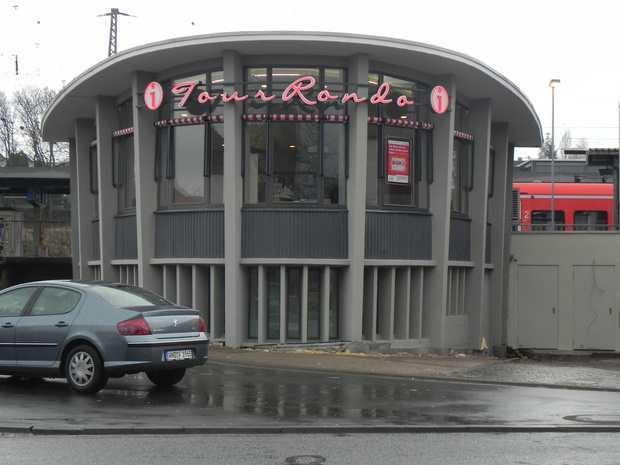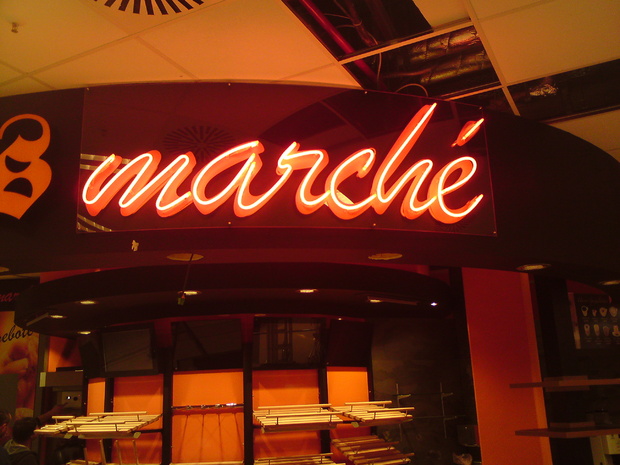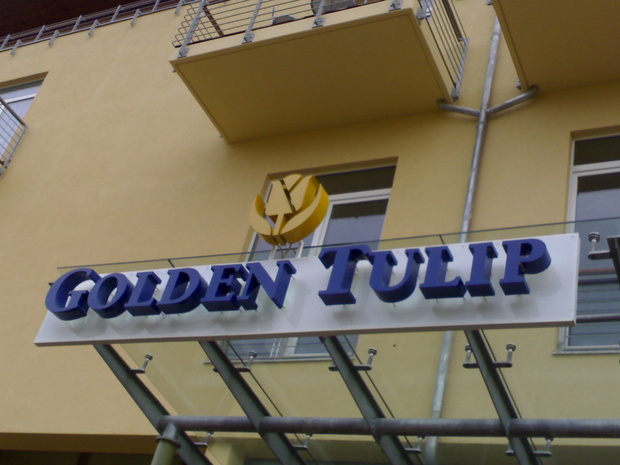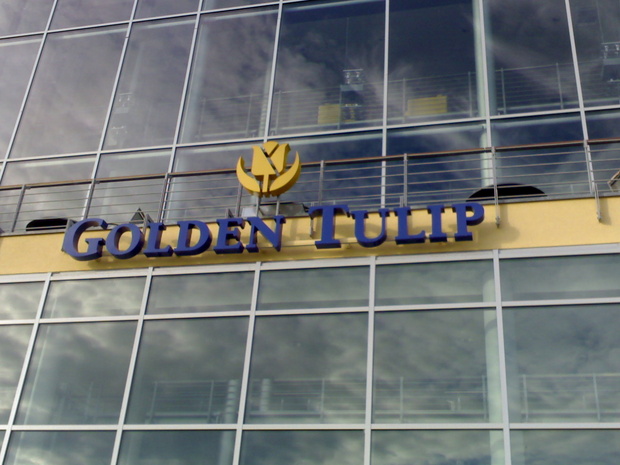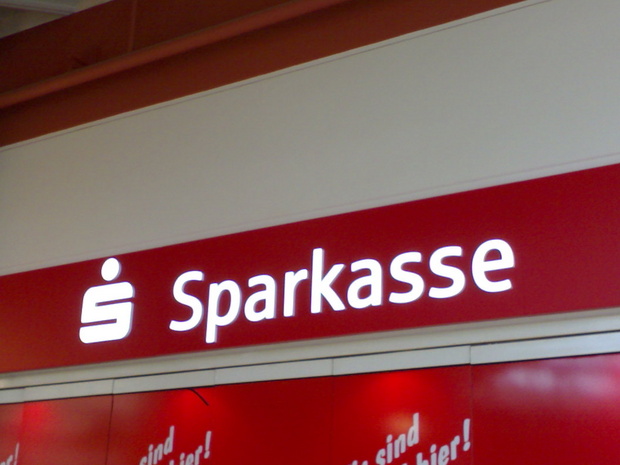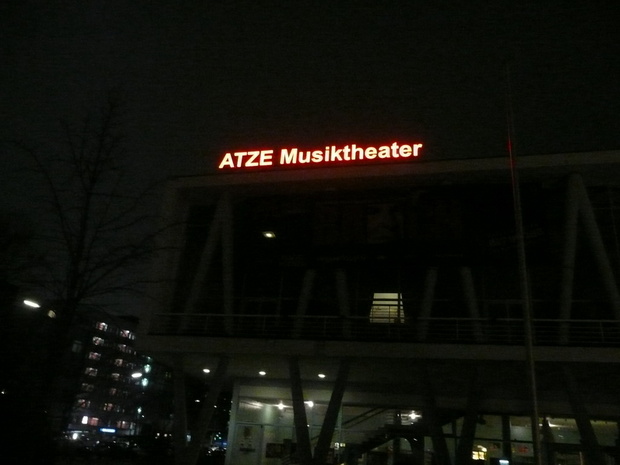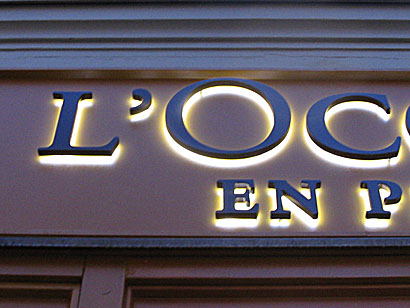
passende Schrift für Hotelbeschriftung gesucht
Hallo liebe Typografinnen und Typografen!
Ich bin dabei ein Hotel zu eröffnen und suche für die Außen-Beschriftung eine passende Schrift. Könntet ihr mir dabei behilflich sein?
Vielen Dank für jede Idee!
Marius Neusteff
Hallo Herr Neusteff,
ich mache professionelle Licht- und Leuchtwerbung in allen Variationen. Angefangen von Acrylglas, mit Neon o. LED, Edelstahl, Kupfer, Titan etc..
Alle Formen und Variationen sind denkbar. Eine edle Variante ist das sogenannte Profil 3-nach hinten an die Fassade strahlend. Nachteil ist dass in der Fernsignalsiation dies nicht so gut lesbar und klar ist wie das Profil 5 nach vorne leuchtend..
Eine KLARE deutliche Schrift erhöht die Lesbarkeit (wichtig z. B. wenn die Autobahn 1 km weit entfernt ist und der Name dort lesbar sein soll)
Denken wir an die vielen einfachen "H O T E L "-Schriftzüge...
Wenn Sie eine schöne Schrift nehmen möchten (z. B. Schreibschrift) wäre das eher was für den Nahbereich, also am Eingang.
Anbei mal ein Bild meines letzten Projektes - natürlich mit Ralfs "i" :)
Anbei mein letztes Projekt (einige erinnern sich noch als ich die passende 50er Jahre Schreibschrift suchte..)
Die Metallbuchstaben (wie in bertels Beispiel) finde ich wesentlich schicker als diese Leuchtreklamekästen, die die meisten Geschäfte/Hotels als Außenwerbung an der Fassade pappen haben. Zumal diese Kästen mit der Zeit oft unansehnlich werden, verschmutzen, nachts Insekten anlocken und deren Neonröhren die Dinger oftmals nicht gleichmäßig ausleuchten. Na gut, das wird inzwischen zum Glück besser und die LED-Lösungen zaubern da oft schon bedeutend schönere Resultate an die Fassaden.
Aber wenn ich die Wahl hätte – ich würde lieber gemalte oder metallene Buchstabenformen verwenden.
Nachtrag: Das muss übrigens man den Bayern und den Briten lassen: Was liebevoll gemalte Logos auf Fassaden und Schildern angeht, sind sie ganz vorne dabei.
LED ist leider ganz stark auf dem Vormarsch und Neon wird mehr und mehr zurück gedrängt..
Es gäbe auch eine Kombination aus gemalten (oder digitalisierten ) Motiven dezent mit LED oder Neon beleuchtet..
LED ist leider ganz stark auf dem Vormarsch und Neon wird mehr und mehr zurück gedrängt...
Warum leider?
LED ist leider ganz stark auf dem Vormarsch und Neon wird mehr und mehr zurück gedrängt …
Wo siehst du bei LED Nachteile? Ich dachte immer die wären länger haltbar, geringer in der Stromaufnahme … hab mich aber wohl zu wenig damit beschäftigt. (Ist eine erst gemeinte Frage).
Die sähe ich auch aus Metall, nachts schön hinterleuchtet, so dass die Typo dunkel bleibt und die Fassade dahinter strahlt. :-)
Hier ein paar sehr edle Oberflächen. Heutzutage kann man ALLE denkbaren Dekore mittels transluzenter Folie auf Acrylglas realisieren.
z.B. Titan poliert, gold, Bronze, Edelstahl etc..
Auch lackiert nach RAL, Pantone (galvanisierter Stahl), Alu etc.
Warum leider?
LED hat sicherlich im Bereich der Stromaufnahme und dem Stromverbrauch große Vorteile. Aber bestimmte Schriften oder Ambiente sind mit LED-Ausleuchtung einfach nicht so darstellbar. Der Charme fehlt einfach. Vergleichbar mit Schallplatte und CD.. ;)
Wo siehst du bei LED Nachteile? Ich dachte immer die wären länger haltbar, geringer in der Stromaufnahme … hab mich aber wohl zu wenig damit beschäftigt. (Ist eine erst gemeinte Frage).
inzwischen gibt es auch LED-Lichtschläuche, die Neon nachahmen. Aber das Licht ist entscheidend und die beiden Neon und LED sind nun mal völlig unterschiedliches Lichtquellen und leuchten unterschiedlich hell und in der Farbe ist völlig unterschiedlich.
LED -> kleine punktförmige, ebene lambertsche Strahler im äquidistanten Raster angeordnet
Neon-> gleichmäßiger, vollkreisförmige lambertscher Strahler auf der gesamten Fläche
Liegt es daran? Bei den Beispielen von Minimalist war auch eine Bauform mit LED-Matrizen vorhanden (LP 10) die geauso aussieht wie ich es immer albträume, weshalb ich ja zu den OLEDs gedeutet habe. Aber für das Abstrahlverhalten einer (Neon-) Röhre ist das auch kein echter Ersatz. Das aufrauhen und diffusieren von LED-Licht ist auch nicht so ohne.